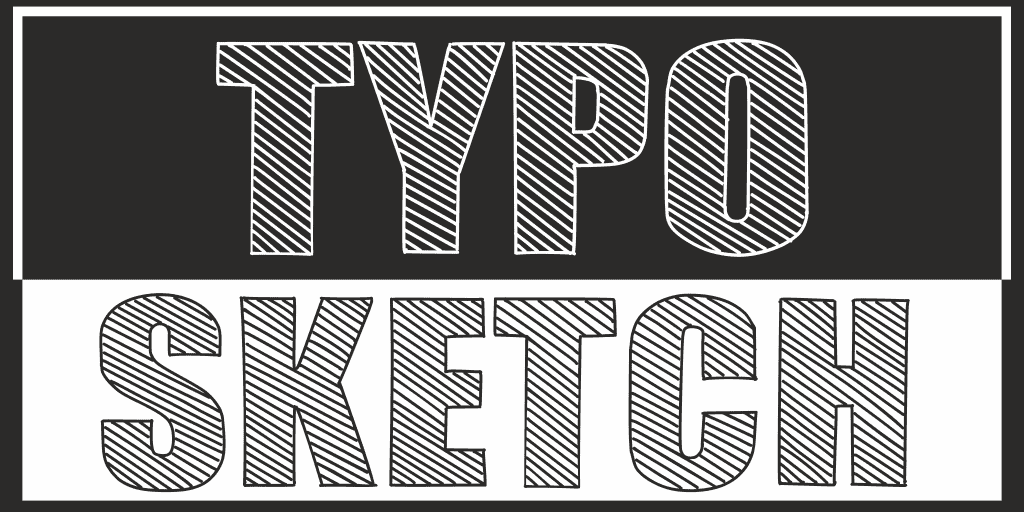
TYPO SKETCH Font
A fonte ‘TYPO SKETCH’ oferece uma experiência visual única e desenhada com cuidado, criando uma atmosfera envolvente que combina a elegância do tipo decorativo com um toque de versatilidade para diversos projetos. Esta fonte foi desenvolvida pelo designer Hamilton, cuja habilidade em criar texturas sofisticadas e formas interessantes torna-a perfeita para aplicativos variados como logotipos, materiais promocionais, design de interiores ou até mesmo gráficos para redes sociais. Com uma escolha cuidadosamente pensada de linhas leves, contrastes marcantes e tons que se adaptam naturalmente a diferentes texturas visuais, esta fonte ‘TYPO SKETCH’ não apenas traz um toque criativo a qualquer projeto, mas também oferece uma maneira única de expressar personalidade para seus projetos digitais. Para aqueles interessados em experimentar o verdadeiro potencial desta fonte, visite www.studiotypo.com/test/typo_sketch_testscreen.html e descubra como ela pode redefinir a forma que suas mensagens são apresentadas online ou offline.